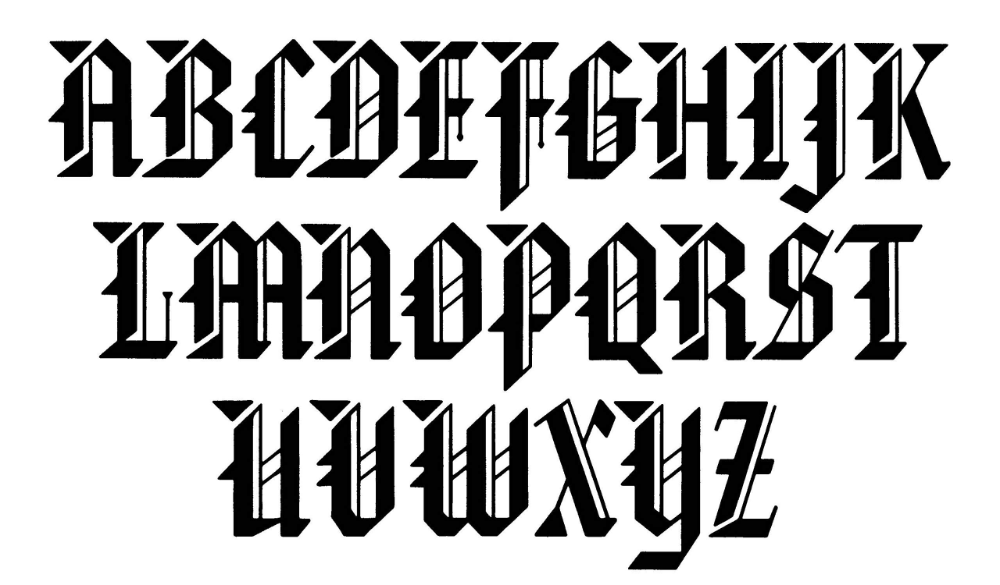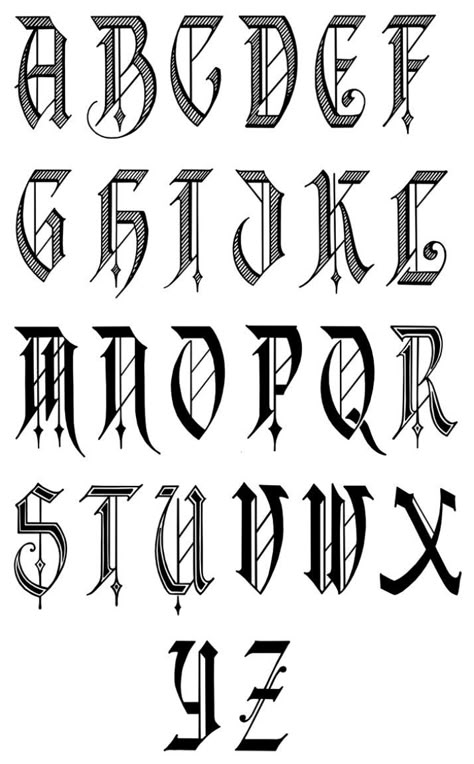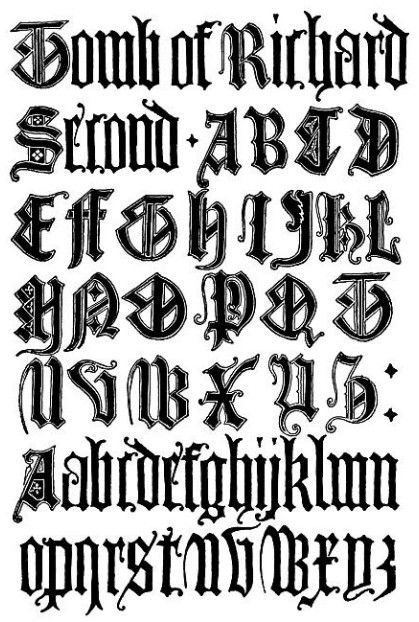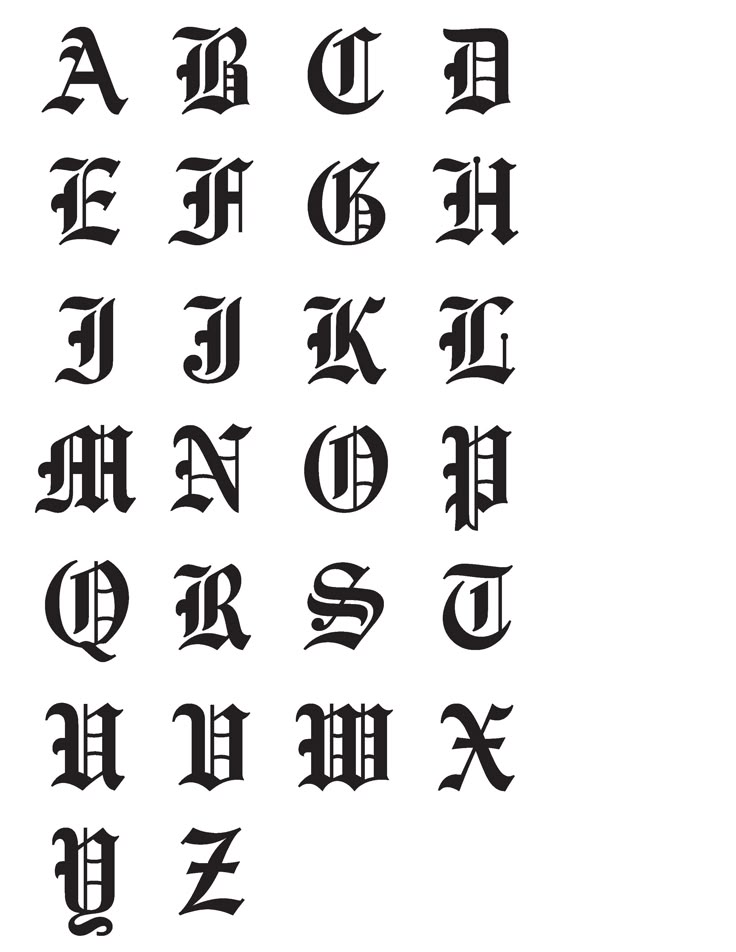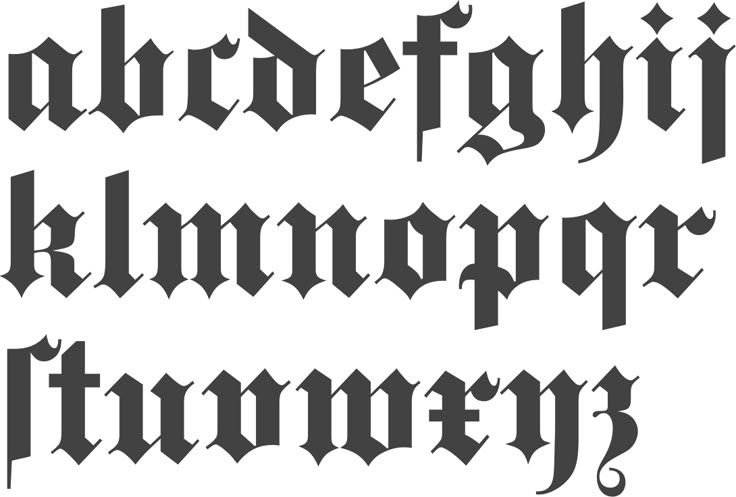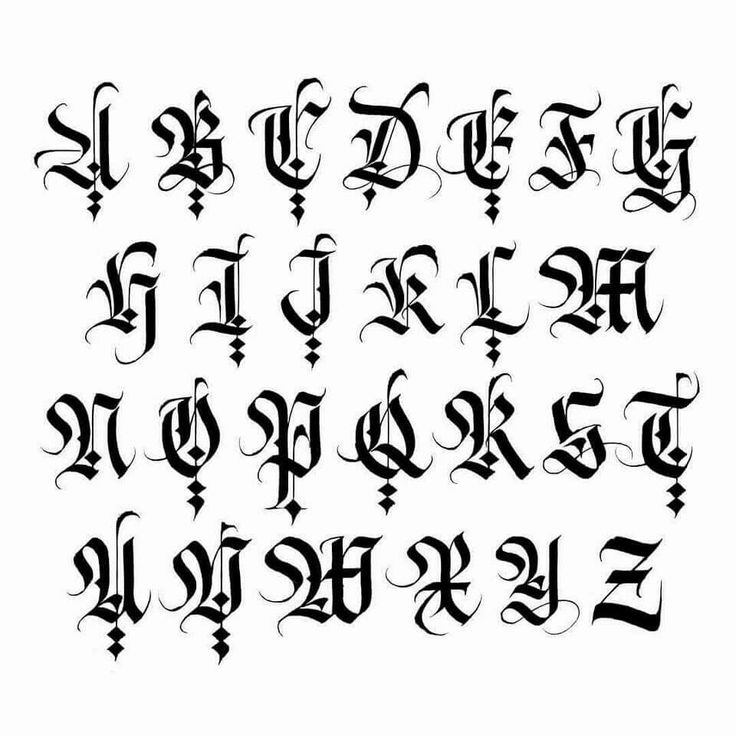
Заинтересовавшись историей шрифтов я постоянно нахожу что-то полезное и интересное, чем и стараюсь поделиться. Сегодня речь пойдет о готических, очень узнаваемых, шрифтах (многие именно с них начинают обучение каллиграфии).
Интересно, что готический стиль написания берет свое начало из греческого алфавита. В 300 г. до н.э. Александр Великий (Македонский) устанавливает греческий язык в качестве единого на огромной территории. Следующая Великая Империя – Римская, переняла удобную греческую письменность, но основным средством общения у римлян стал латинский язык с его прямым антиквенным шрифтом (здесь впервые появились засечки на заглавных буквах (капителях) – serifs). Латынь была заимствована у этрусков, буквы которых, в свою очередь, основывались на греческом алфавите.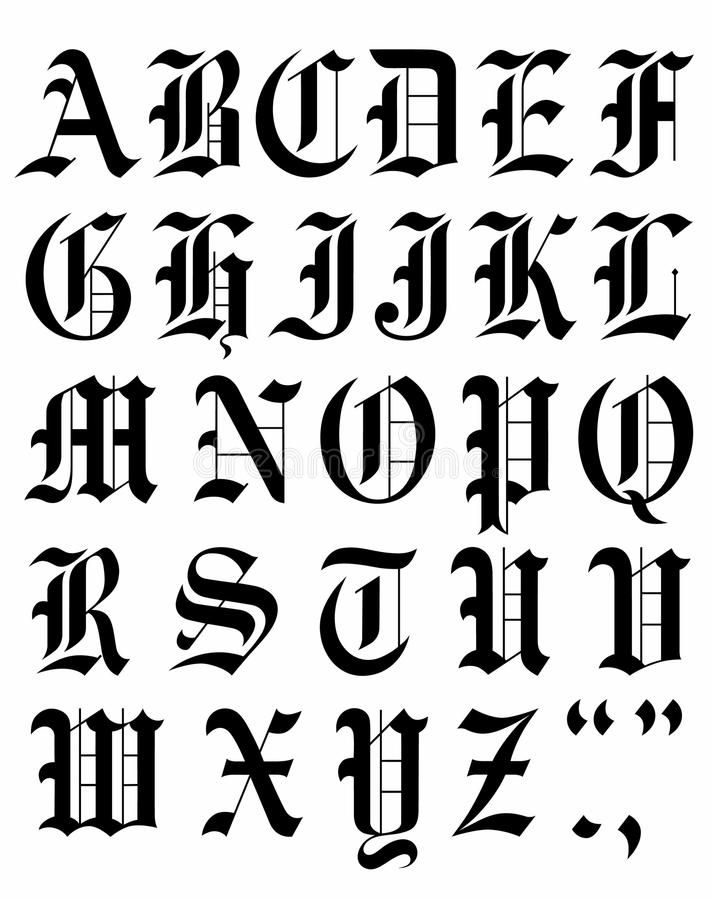
В 395 г. н. э. в конце правления императора Константина, Римскую Империю наводнили германские варвары, уже имевшие к тому времени свой рунический алфавит, который называют также футарком (futhark). Вот образец рунического алфавита готских (германских) тевтонов.
Благодаря распространению христианства в этот момент появляется необходимость в книгах и появляются тысячи монахов переписчиков, которые постепенно модифицировали написание шрифта и создавали новые стили.
Ниже приведен пример кельтского письма, называемого унциальным (scriptura uncialis), потому, что литеры записывались на четырёх направляющих линиях, отстоящих друг от друга на расстоянии одной унции (24,5 мм). Кельты сделали римское написание букв мягче и выразительнее
Дальнейшее развитие унциального письма привело к появлению четырёх форм: ирландское письмо (Ирландия и Англия), меровингское (Франция), вестготское (Испания) и старо-италийское (Италия).
Между 900 и 1000 г.г. наиболее развитое меровингское письмо преобразовалось в каролингское, ставшее нормой для переписывания церковных книг. Это письмо характерно появлением маленьких (то, что мы теперь называем “строчными”) букв. К концу 1000 г. н. э. из каролингского развилось романское письмо (Romanesque), которое к 1200 г. приобрело уже почти готический вид. Он и теперь известен под именем
Ранний готический шрифт (протоготический) – был широко распространен в западной Европе и использовался со второй половины 11 века до середины 13 века, в период между концом каролингской эпохи и началом готической. Поэтому может рассматриваться как переход от каролингского минускула к текстуре, т.к. сочетает в себе элементы этих написаний.
Тексту́ра (от лат. textura — ткань, также textura quadrata, Blackletter, Old English) — основная разновидность готического письма.
Словосочетание «готический шрифт», как правило, ассоциируется именно с этим вариантом. Появилась в начале 13 века. Своё название текстура получила за то, что покрывала страницу равномерно и на определённом расстоянии страница, заполненная таким шрифтом, напоминала текстуру ткани. Характерное отличие шрифтов данного типа — вытянутость букв. Шрифт представлял собой революционные изменения в каллиграфии – после столетий акцента на четкое распознавание письма, отдельные буквы были внезапно подчинены общему текстурному эффекту. Textura Prescisus – развивался параллельно с textura quadrata.Появился предположительно на юге Англии и распространился во Франции. К шрифту относится выражение «vel sine pedibus» (лат. «без ног»), т.к. отличается плоским квадратным основанием основного штриха.
Bastard Secretary – чем более формальным становился манускриптный шрифт, тем больше была необходимость в более функциональных шрифтах в дополнение к ним. Поэтому изысканные текстурные шрифты дали начало шрифтам для менее престижного, повседневного письма.
Несколько взаимодополняющих написаний развивались как на региональном, так и на национальном уровне, быстро превращаясь в полноценные шрифты. И классифицировались они как «гибридные» (bastarda), термин, обозначающий шрифты смешанного скорописного и текстурного происхождения.
Подобное явление, предположительно, взяло начало в конце 12 века, для оформления документов. Мне очень нравится этот шрифт сочетанием массивных штрихов и тонких изящных декоративных линий. Batarde (Lettre Bourguignonne) – французский эквивалент английского Bastard Secretary. Был разработан в конце 13 века и использовался вплоть до середины 16, развился из скорописного в полноценный формальный шрифт. Достиг своей самой сложной формы в середине 15 века, в эпоху, когда популярность печатных книг все более возрастала среди широких слоев населения. В такой форме был уважаем в Бургундских придворных кругах, откуда и второе название. Фракту́ра (нем. Fraktur — надлом, German letter) — поздняя разновидность готического письма, первые рукописные примеры датируются примерно 15 веком, печатная версия появилась веком позже.
Являет собой смесь немецкой скорописи и текстуры. Ранние варианты появились как народные, общеупотребительные написания, и позже были взяты за основу для многих печатных шрифтов. Швабахер, швабах (нем. Schwabacher) — разновидность готического письма, зародилась в 15 веке. Ломаное письмо с округлёнными очертаниями некоторых букв. Этот шрифт доминировал в Германии с конца 15 до середины 16 века. После чего был заменён на фрактуру, но оставался популярным до 20 века. Похож на текстуру, но более округлую, простую версию. Роту́нда (итал. rotonda — круглая) — итальянский вариант готического письма (полуготический шрифт), появившийся в XII веке. Отличается округлённостью и отсутствием надломов. Получил начало от каролингского минускула. Готическое влияние на написания восточной Европы между 10 и 13 веками получило сильнейшее сопротивление в Италии. Четкие формы классических написаний, использование каролингского минускула способствовали появлению шрифта, отличающегося от готического более круглыми, открытыми формами и короткими выносными элементами.
Был распространен вплоть до 18 века, в том числе получил широкое распространение в Испании. Ротунда явилась уже переходным шрифтом от готики к антикве. На севере Европы, особенно в Германии, шрифты “настоящей готики” постепенно переродились в более широкие и удобочитаемые литеры “поздней готики”.
Безмерный вклад в то, что готический шрифт до сих пор легко узнаваем и популярен, сделал Иоганн Гутенберг (Iogann Gutenberg). Прежний процесс переписи целой книги вручную был утомителен, трудоёмок, как следствие книги стоили баснословно дорого и были редки. Изобретение же Гутенберга – печатный станок и многократное использование отдельных свинцовых буквенных литер, позволило за 10 лет наводнить всю Европу печатными лавками и книжными ярмарками.
Каждая литера проектировалась Гутенбергом отдельно и гравировалась вручную в твёрдом металле. Эта основополагающая технология горячего металлического литья получила исключительное распространение, совершила переворот в системе коммуникаций Запада и применялась вплоть до 60-х годов XX-го века.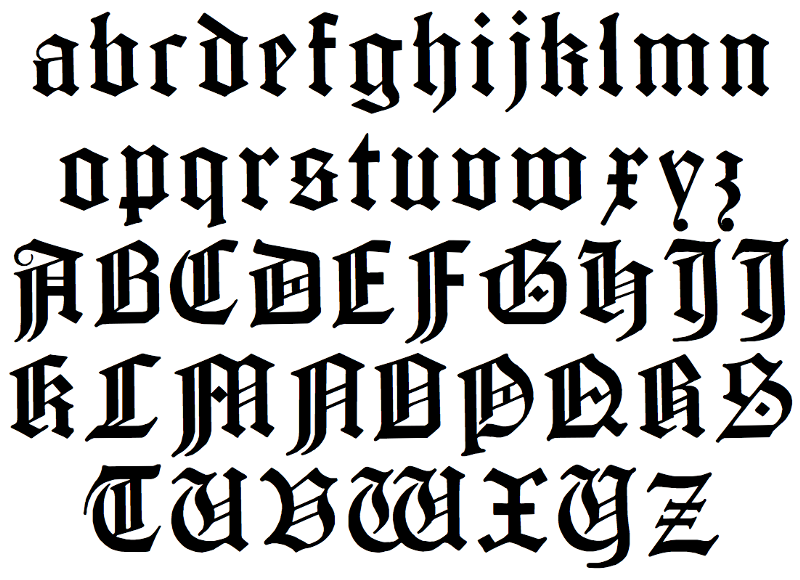
Для первых отливок литер Гутенберг выбрал готический шрифт, как господствующую форму рукописного шрифта того времени. Разработал этот шрифт Петер Шеффер (Peter Shoeffer) под наблюдением Гуттенберга. Шрифт был точной имитацией самого совершенного письма той эпохи. Он содержал около 300 знаков, лигатур, сокращений. Впервые шрифт Гуттенберга был использован для издания 42-х страничной Майнцкой Библии (Mainz Bible).
Признаться, пока я не интересовалась этим, мне казалось, что готическое письмо все одинаковое, а выяснилось, что столько разных интересных вариантов.
Если вы хотите попробовать скопировать образцы из поста, вам пригодится ручка Parallel Pen, маркеры с плоским пером или обычное плоское перо. В старину использовались специальным образом заточенные перья, но благо технологии позволяют сегодня упростить этот процесс. Если вы уже пробовали писать готические шрифты — делитесь впечатлениями и картинками.
#история #каллиграфия #готические_шрифты #написание #готика #книгопечатание #ротунда #леттеринг #текстура #фрактура #письменность
40 лучших староанглийских шрифтов (Blackletter, Gothic)
Vandelay Design может получать компенсацию от компаний, продуктов и услуг, представленных на нашем сайте.
Для получения более подробной информации, пожалуйста, обратитесь к нашей странице раскрытия информации.
Староанглийские шрифты — отличный способ добавить характер и шарм любому дизайну. Самое приятное, что существует множество различных вариаций и стилей. Эти шрифты иногда называют Blackletter или Gothic, но как бы вы их ни называли, у них есть особый характер, который добавит вашему дизайну.
НЕОГРАНИЧЕННАЯ ЗАГРУЗКА: более 50 миллионов шрифтов и элементов дизайна
Лучшие древнеанглийские шрифты
Вам нужен шрифт для вашего веб-сайта или проекта, напоминающий средневековье? Вы хотите вызвать чувство тайны, ужаса и трепета с помощью замысловатого дизайна букв? Если да, вот лучшие шрифты на выбор.
Если вы любите шрифты, вам обязательно стоит попробовать Envato Elements. Подписавшись на Elements, вы получите неограниченное количество загрузок 25 000 шрифтов , плюс миллионов других ресурсов , таких как темы WordPress, стоковые фотографии, графика, звуковые эффекты и многое другое.
Это лучшая ценность, которую вы можете найти в индустрии дизайна.
Cambridge
Cambridge — жирный и декоративный шрифт в готическом стиле. Ручной шрифт имеет красивый стиль, который хорошо подходит для полиграфического дизайна, обложек книг, логотипов и брендинга, музыкальных плакатов, обложек альбомов и многого другого. Пакет включает прописные и строчные буквы, цифры, знаки препинания, альтернативные символы и веб-шрифт.
Шрифт Clockwork Blackletter
Clockwork — удивительный шрифт Blackletter с винтажным оттенком. Он отличается современным викторианским почерком, который сочетает в себе современную и классическую типографику. Вам понравятся альтернативы и лигатуры, с помощью которых можно легко и красиво оформить текст. Вы получите прописные и строчные буквы, многоязычную поддержку и веб-шрифт для дополнительной универсальности.
Lordish
Lordish — выдающийся шрифт Blackletter, представленный в трех вариантах плотности: тонкий, легкий и обычный.
Этот уникальный шрифт идеально подходит для татуировок, обложек альбомов, футболок, плакатов, дизайнов флаеров, товаров и многого другого. Бонусные украшения включены в загрузку, а также доступен веб-шрифт.
Vadderick
Vadderick — потрясающий шрифт, в котором используется старинная каллиграфия для создания яркого и запоминающегося образа. Этот элегантный шрифт напоминает о средневековье. Он поставляется с прописными и строчными буквами, цифрами, пунктуацией и веб-шрифтом.
Snubhore
Snubhore — оригинальный готический шрифт Blackletter с большим количеством стилей. Это все заглавные буквы с цифрами и знаками препинания. Это идеальный выбор для брендинга, этикеток, одежды, упаковки и многого другого.
The Wednesday
Wednesday — стильный декоративный шрифт, который идеально подходит для этикеток, плакатов, товаров, брендинга и татуировок. Обширный пакет включает прописные и строчные буквы, стилистические варианты, цифры, знаки препинания, символы валюты, глифы и многоязычную поддержку.
Доступна версия веб-шрифта.
Engravers Old English
Engravers Old English FS выпускается двух начертаний (средний и полужирный) и имеет безошибочное ощущение древнеанглийского.
Candelabra
Candelabra — это средневековый шрифт Blackletter, который вам обязательно понравится. Это отличный выбор для татуировок, искусства групп, игрового дизайна, обложек книг, футболок, кепок и многого другого. Пакет включает в себя прописные и строчные буквы, цифры, знаки препинания, лигатуры, а также некоторые бонусные блики и стили слоев для украшения вашего текста. Доступен веб-шрифт.
Osgard Pro
Osgard Pro — это роскошный шрифт с возможностями OpenType, который идеально подходит, когда вам нужен выделяющийся шрифт. С элементами романской типографики и готического стиля Blackletter этот шрифт обязательно станет одним из ваших любимых. Огромный пакет включает в себя обычные и трафаретные версии, прописные и строчные буквы, цифры и более 1000 росчерков для неограниченных декоративных возможностей.
Также доступен веб-шрифт.
Carol Gothic
Carol Gothic — это традиционный шрифт Blackletter с древнеанглийскими характеристиками и стилем. В викторианском стиле он идеально подходит для тематических дизайнов 19 века. Это идеальный выбор для этикеток и упаковки продуктов, брендинга, одежды и многого другого.
The Bjorke
The Bjorke — стильный рукописный шрифт. Это отличный выбор для татуировок, обложек книг, плакатов и других печатных рисунков. Загрузка включает в себя обычную и альтернативную версии, а также веб-шрифт.
Новый староанглийский
Новый староанглийский язык был вдохновлен текстом на викторианских монетах. Его легко читать, но он сохраняет ощущение староанглийского и Blackletter. Он поставляется в одном весе с цифрами, пунктуацией и глифами.
Bullgine
Bullgine — современный готический шрифт Blackletter. Это подходящий выбор для одежды, логотипов и брендинга, обложек альбомов и рекламы. Загрузка включает прописные и строчные буквы, цифры, знаки препинания, многоязычную поддержку и стилистические варианты.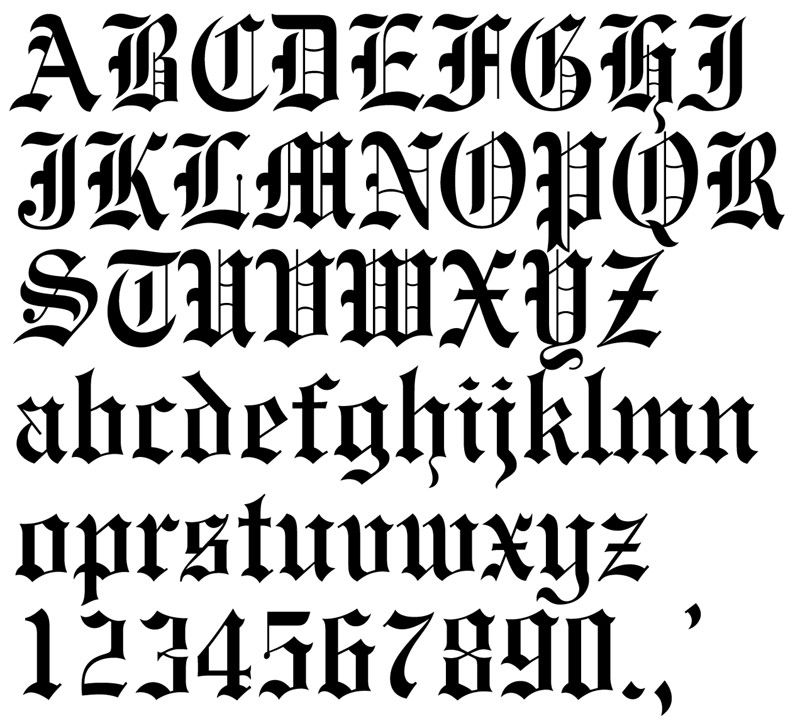
Aceking
Aceking — это винтажный дисплейный шрифт с неоспоримым средневековым влиянием. Вы можете использовать Aceking для книг, фильмов, игр, одежды, постеров групп и многого другого. Это шрифт с заглавными буквами, в котором есть цифры, знаки препинания и веб-шрифт.
Blackside
Blackside — потрясающий шрифт Blackletter с альтернативными вариантами, позволяющими легко добавить декоративный штрих к индивидуальному виду. Он также включает прописные и строчные буквы, цифры, знаки препинания, многоязычную поддержку и веб-шрифт.
Cloister Black CT
Если вы ищете типичный староанглийский шрифт, Cloister Black CT может быть правильным выбором. Первоначально разработанный в 1904 году, этот шрифт по-прежнему актуален и полезен более 100 лет спустя.
Mortal
Вдохновленный татуировками и уличным искусством, Mortal — это шрифт, который хорошо подходит для татуировок, логотипов, брендинга, значков, этикеток, футболок и многого другого.
Есть два варианта с прописными и строчными буквами, цифрами, пунктуацией и альтернативными символами. Доступен веб-шрифт.
Fullerton Next
Fullerton Next — ремейк шрифта Fullerton. Он поставляется с прописными и строчными буквами, цифрами, пунктуацией, символами, многоязычной поддержкой и альтернативными символами. Также доступен веб-шрифт.
Avestrava Regular
Avestrava Regular — это современный шрифт, вдохновленный староанглийским стилем и шрифтом. В пакет входят прописные и строчные буквы, лигатуры, символы для других языков и дополнительные украшения для украшения вашего текста. Он идеально подходит для большого текста в таких проектах, как татуировки, брендинг, этикетки, дизайн упаковки, футболки, другая одежда и многое другое.
Volantis
Volantis — это винтажный шрифт Blackletter, который отлично подходит для заголовков, журналов, газет, татуировок, этикеток, постеров групп и многого другого. Он имеет закодированные символы PUA, что означает, что его можно использовать в любом программном обеспечении.
Многоязычная поддержка включена для многих языков (африкаанс, албанский, каталанский, чешский, датский, голландский, английский, эстонский, финский, французский, немецкий, венгерский, итальянский, латышский, литовский, норвежский, польский, португальский, словацкий, словенский, испанский, Шведский). Веб-шрифт также включен.
Phoenix
Phoenix — красивый готический шрифт. Он включает прописные и строчные буквы, а также стилистические варианты. Вам понравится использовать Phoenix для дизайна татуировок, логотипов и брендинга, приглашений, дизайна меню, одежды и многого другого.
Old Charlotte
Old Charlotte отличается жирным шрифтом, вдохновленным средневековой готикой. Он отлично подходит для обложек книг, постеров фильмов, видеоигр, обложек альбомов, татуировок и многого другого. Загрузка включает прописные и строчные буквы, цифры, знаки препинания, альтернативные символы и веб-шрифт.
Blonde
Blonde — это современное семейство шрифтов Blackletter, которое включает варианты шрифтов с засечками и без засечек.
Он идеально подходит для брендинга, татуировок, обложек альбомов, футболок, рук и моды. Доступна версия веб-шрифта.
ROOTKING
ROOTKING был вдохновлен тонкими и толстыми штрихами древнеанглийской типографики. Он идеально подходит для заголовков, плакатов, афиш концертов, обложек альбомов, обложек видеоигр, пивных этикеток и многого другого. Загрузка включает в себя обычную версию, а также орнаменты, символы, знаки препинания, цифры и многоязычные символы. В качестве отображаемого шрифта он лучше всего подходит для крупного текста.
Cattedrale
Cattedrale — великолепный готический шрифт, который поставляется в потрясающей упаковке. Существует четыре шрифта (обычный, нарезанный, грубый и контурный), чтобы выбрать нужный дизайн букв. Вы также получите выдающуюся коллекцию украшений для завершающих штрихов вашего дизайна. С четырьмя стилями на выбор и украшениями в вашем распоряжении легко создать индивидуальный образ.
Cydonia
Cydonia — красивый шрифт Blackletter, который идеально подходит для дизайна брошюр, брендинга, одежды, товаров, рекламы и многого другого.
Он содержит закодированные символы PUA для работы в любом программном обеспечении, а также включает многоязычную поддержку нескольких языков. Также предоставляется веб-шрифт.
Black Seeds
Black Seeds — это шрифт Blackletter, отличающийся внешним видом и стилем. Он был вдохновлен современной каллиграфией и готическим шрифтом. Используйте Black Seeds для создания татуировок, логотипов, плакатов, обложек альбомов, обложек фильмов, обложек книг и многого другого. Загрузка включает прописные и строчные буквы, цифры, знаки препинания, символы, многоязычную поддержку и веб-шрифт.
Полиэстер
Полиэстер представляет собой сочетание современной и классической типографики. Вам понравится коллекция альтернатив, которые делают этот шрифт очень увлекательным в использовании. Полиэстер — это тот, который вы обязательно будете использовать довольно часто. Также доступен веб-шрифт.
Rozex
Rozek — это декоративный рукописный шрифт, вдохновленный средневековой готической типографикой.
Его можно использовать для создания татуировок, обложек книг, одежды, логотипов и многого другого. Загрузка поставляется с прописными и строчными буквами, цифрами, пунктуацией, альтернативными символами, лигатурами и веб-шрифтом.
Алабаста
Алабаста содержит закодированные символы PUA, поэтому его можно использовать в любом программном обеспечении. Вы также получите многоязычные символы для огромного выбора языков, а также веб-шрифт.
Andalusia
Andalusia — уникальный шрифт от того же дизайнера, что и Alabasta. Он также предлагает закодированные символы PUA и обширную многоязычную поддержку. Версия веб-шрифта включена в загрузку.
Gematype
Gematype — это современный шрифт Blackletter, который идеально подходит для логотипов и брендинга, этикеток и упаковки продуктов, татуировок, значков, дизайнов футболок и многого другого. Он поставляется с прописными и строчными буквами, цифрами, знаками препинания, ударениями (многоязычные символы), а также в качестве бонуса декоративный векторный файл.
Также доступна версия веб-шрифта.
Amador
Amador — это сокращенный шрифт Blackletter в формате Open Type. Он поставляется в одном весе с включенными глифами и поддержкой огромного количества языков.
Бесплатные староанглийские шрифты
До сих пор мы рассматривали лучшие староанглийские шрифты премиум-класса. Приведенные выше варианты идеальны, но, возможно, вы ищете бесплатный шрифт, который можно использовать бесплатно. В качестве предостережения всегда проверяйте условия лицензии и ограничения, когда используете бесплатные программы. С учетом сказанного, вот наши любимые бесплатные древнеанглийские шрифты.
Chomsky
Chomsky — шрифт для заголовков газет в стиле New York Times.
Kingsthings Italique
Kingsthings Italique — красивый каллиграфический шрифт со староанглийским шармом.
Canterbury
Canterbury — это бесплатный шрифт Blackletter с определенным средневековым оттенком.
PlainBlack
PlainBlack предлагает большую упаковку, включающую шесть вариантов, в том числе с прорезями и тиснением.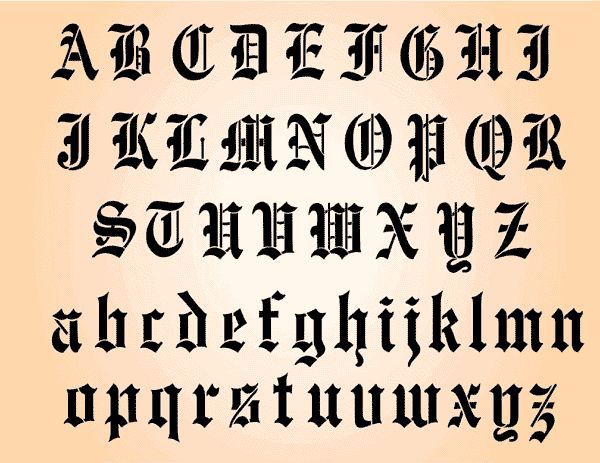
Староанглийская пятерка
Old English Five — типичный староанглийский шрифт.
Genzsch Et Heyse
Genzsch Et Heyse — красивый шрифт, представленный в двух вариантах (обычный и альтернативный).
Заключительные мысли о староанглийских шрифтах и шрифтах Blackletter
Староанглийские шрифты могут не подходить для всех ваших дизайнерских проектов, но в правильной ситуации они идеальны. Когда вам нужен шрифт, который соответствует атрибутам дизайна, типичным для шрифтов Gothic и Blackletter, у вас будет множество вариантов.